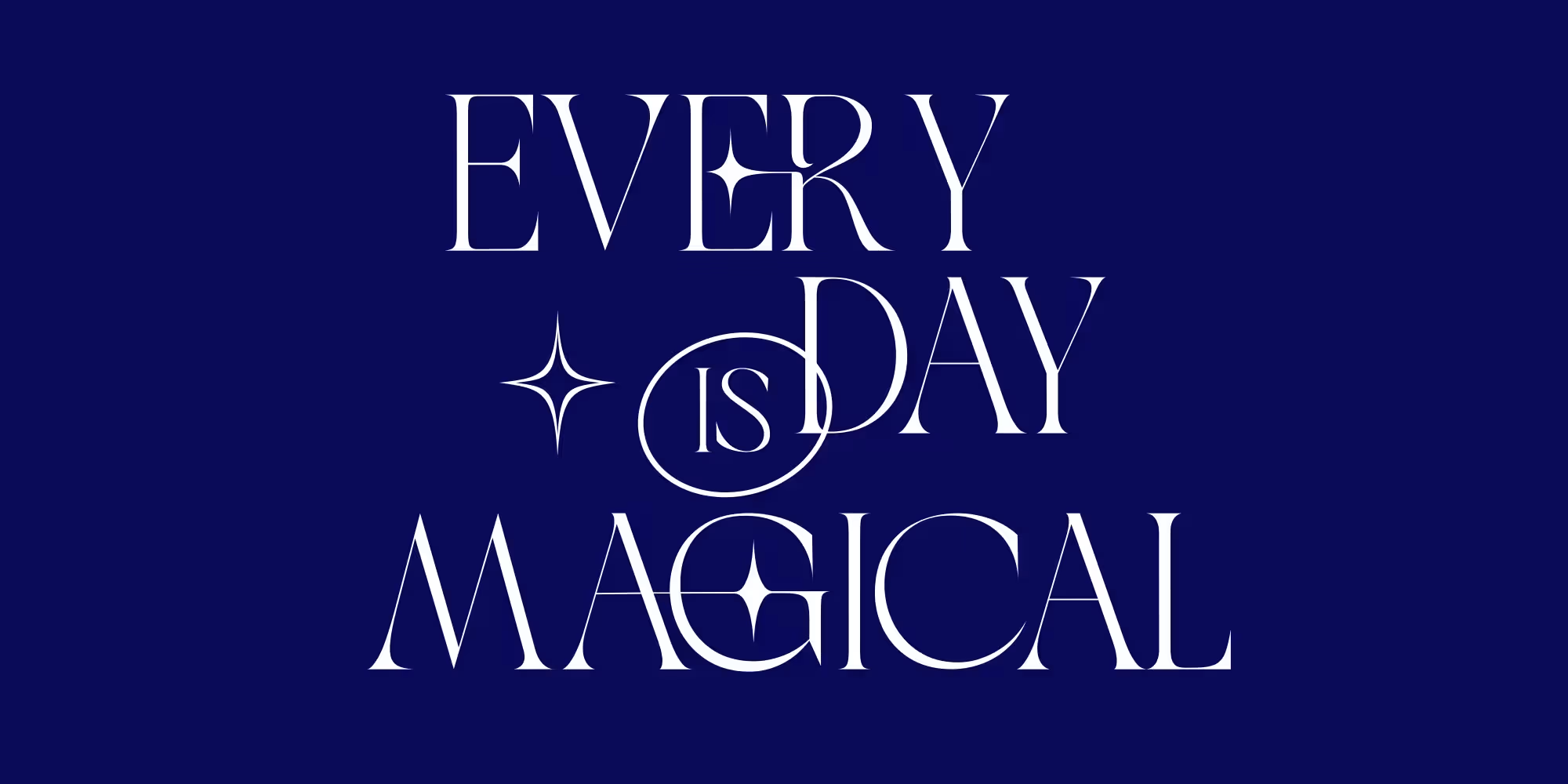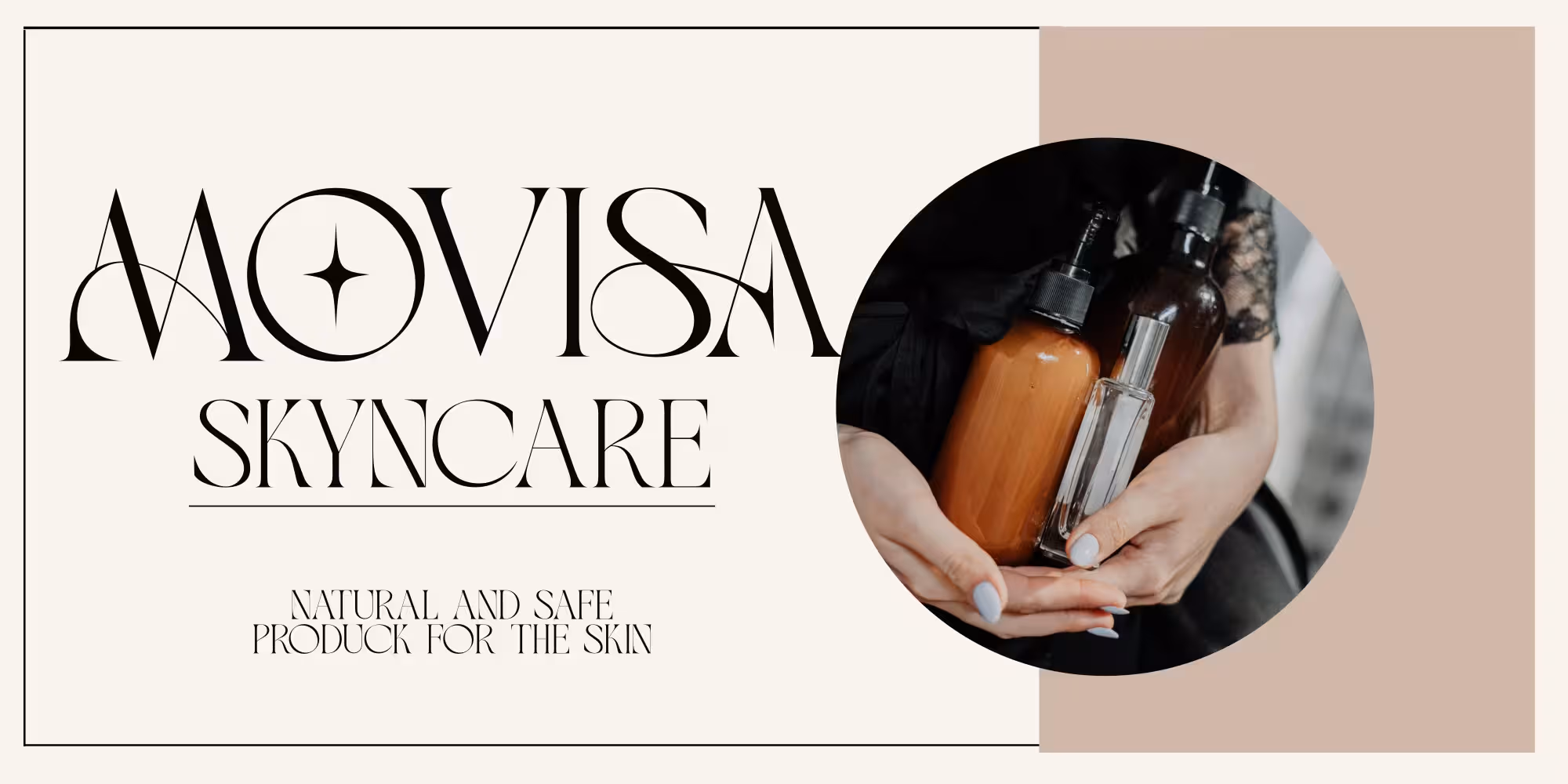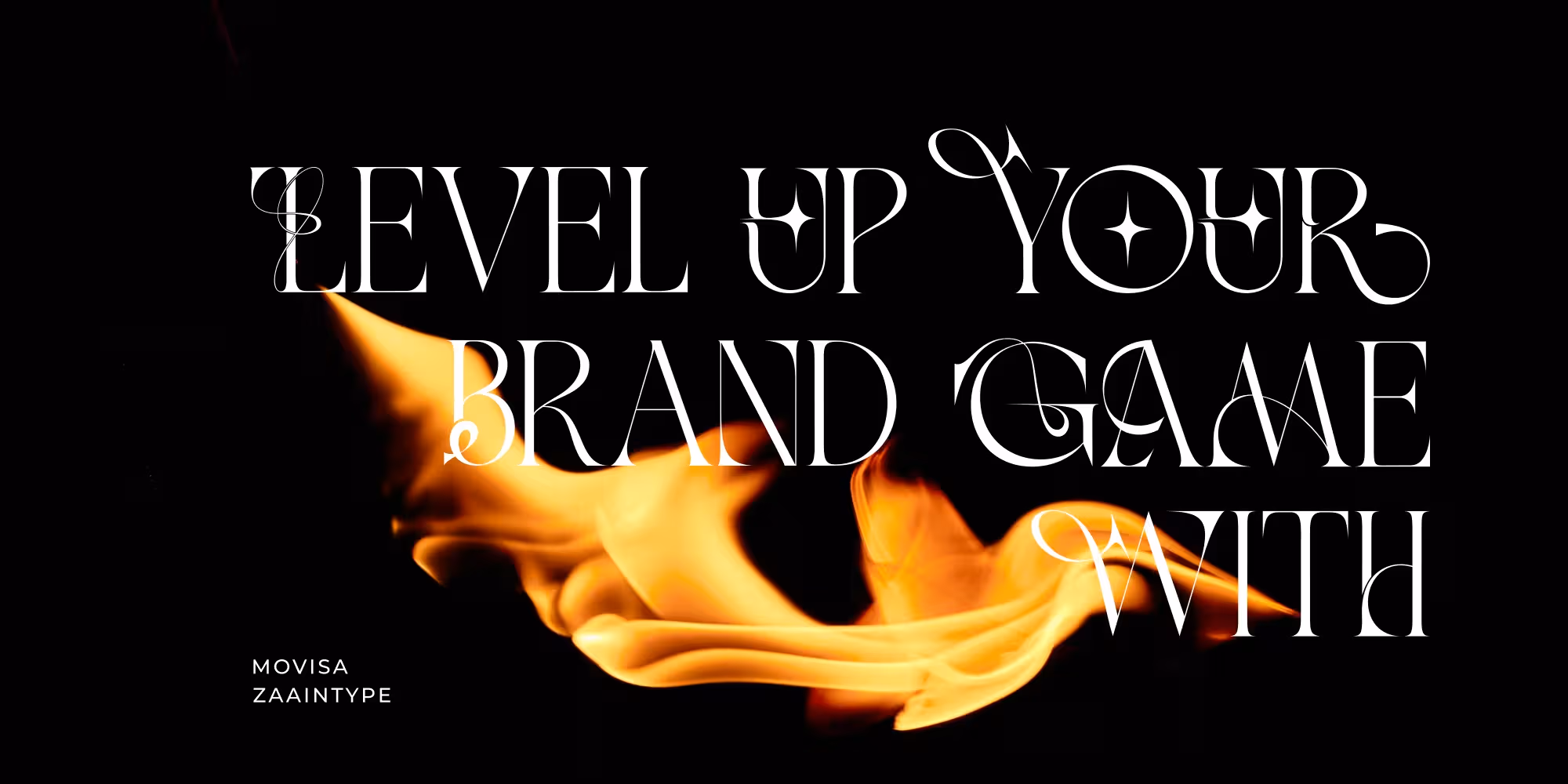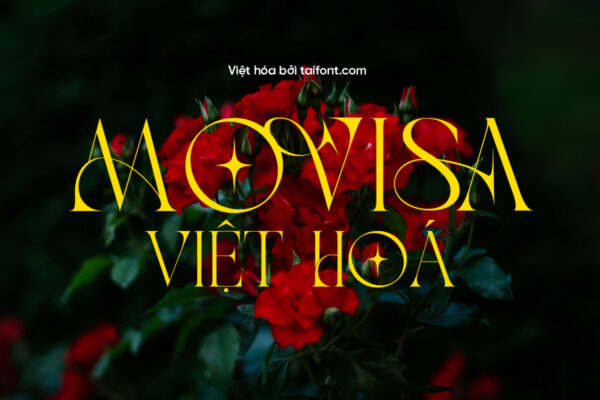
Giới thiệu về Font TF Movisa Việt hóa
TF Movisa Việt hóa là một font chữ có chân (serif) nổi bật với vẻ đẹp sang trọng, tinh tế và đầy quyến rũ. Font này được thiết kế với những đường nét thanh lịch, mềm mại nhưng vẫn giữ được sự rõ ràng và chuyên nghiệp, toát lên phong thái quý phái và đẳng cấp, lý tưởng để tạo nên sự độc đáo cho mọi thiết kế.
Với sự tinh xảo trong từng ký tự và tính thẩm mỹ vượt trội, Movisa là lựa chọn hoàn hảo cho các ấn phẩm cần sự sang trọng và khác biệt, đặc biệt là trong các lĩnh vực:
- Thiết kế đám cưới: Hoàn hảo để viết tên cô dâu chú rể, lời mời, hoặc các thông tin chi tiết trên thiệp cưới, menu tiệc, bảng tên khách mời. Nét chữ thanh lịch và duyên dáng sẽ biến mỗi tấm thiệp thành một tác phẩm nghệ thuật, mang đậm dấu ấn cá nhân và sự lãng mạn, trang trọng cho ngày trọng đại.
- Thiết kế thời trang: Lý tưởng cho các thương hiệu thời trang cao cấp, từ logo, nhãn mác sản phẩm, lookbook, đến các chiến dịch quảng bá bộ sưu tập. Font này giúp truyền tải vẻ đẹp thanh lịch, đẳng cấp và độc đáo của trang phục, nâng tầm giá trị thương hiệu.
- Thiết kế tạp chí: Phù hợp để sử dụng cho các tiêu đề chính, lời dẫn, hoặc nội dung bài viết trong các tạp chí về thời trang, nghệ thuật, kiến trúc, hoặc lối sống. Nét chữ có chân của Movisa giúp tăng tính trang trọng và dễ đọc, đồng thời tạo cảm giác cao cấp, thu hút độc giả.
- Thiết kế nhận diện thương hiệu: Phù hợp cho logo, tagline hoặc bộ nhận diện thương hiệu muốn truyền tải sự tinh tế, uy tín và sự thanh lịch. Movisa giúp xây dựng một hình ảnh thương hiệu vững chắc và dễ nhận diện.
Với TF Movisa Việt hóa, bạn có thể dễ dàng thổi hồn tinh tế, sang trọng và vẻ đẹp hoàn hảo vào các thiết kế, tạo ra những sản phẩm không chỉ đẹp mắt mà còn đầy cảm xúc và sức hút đặc biệt.